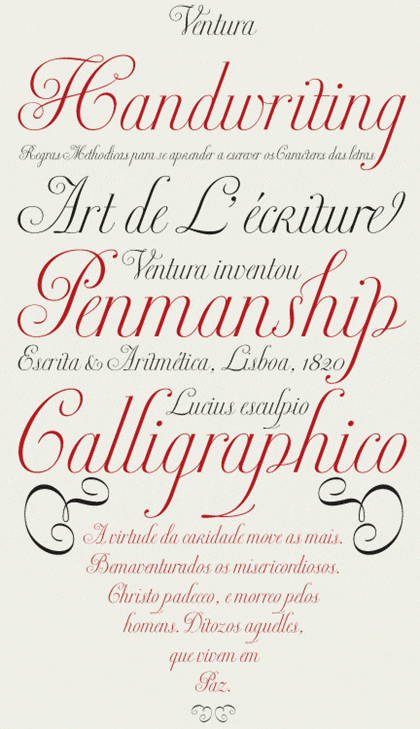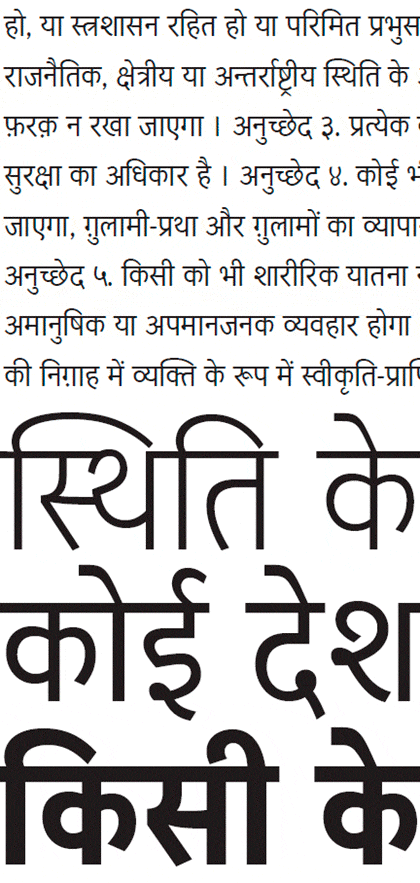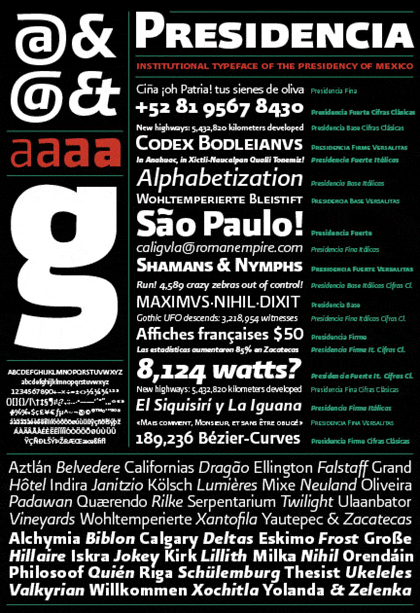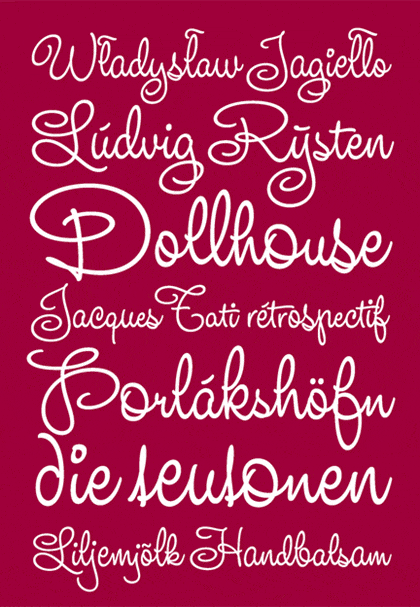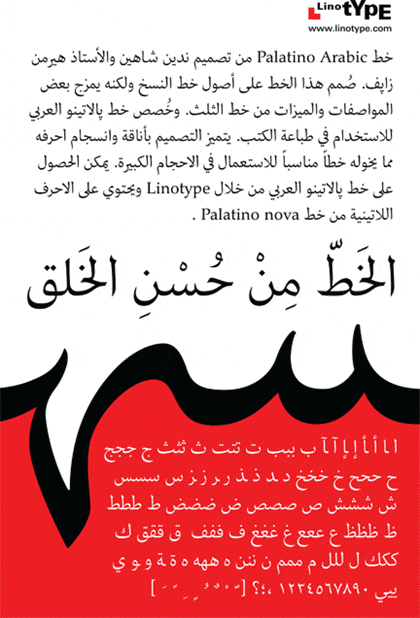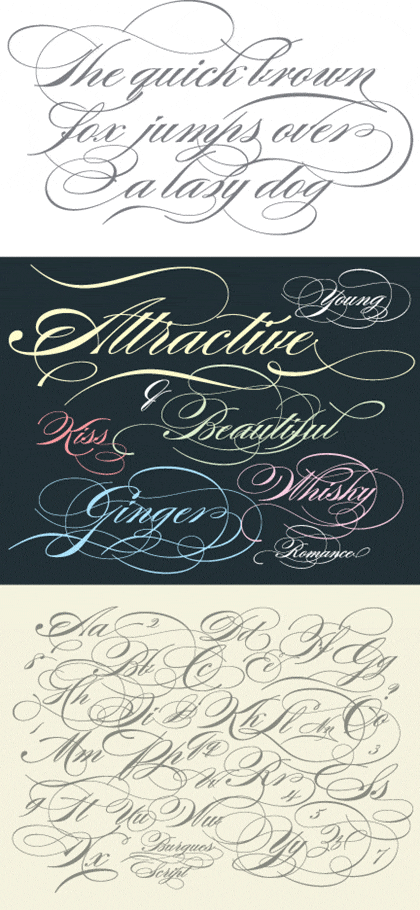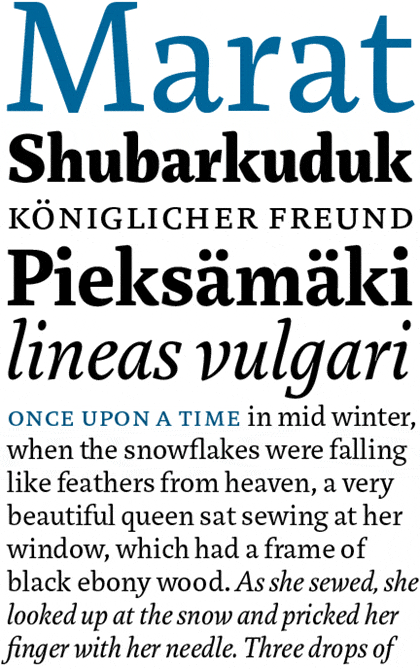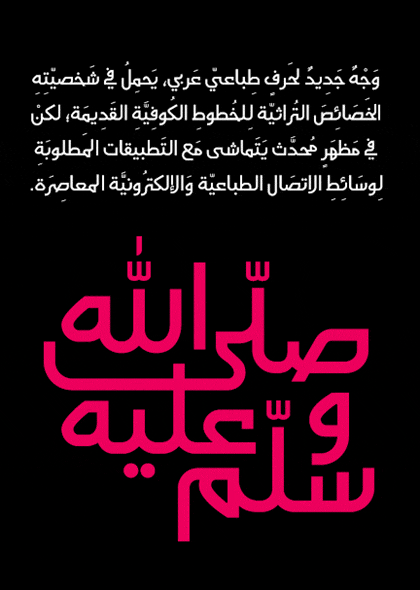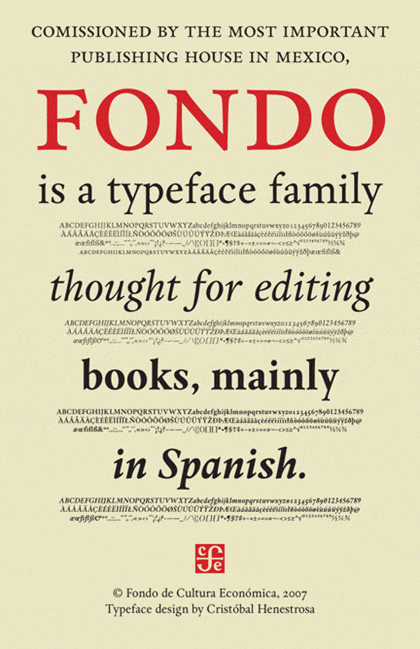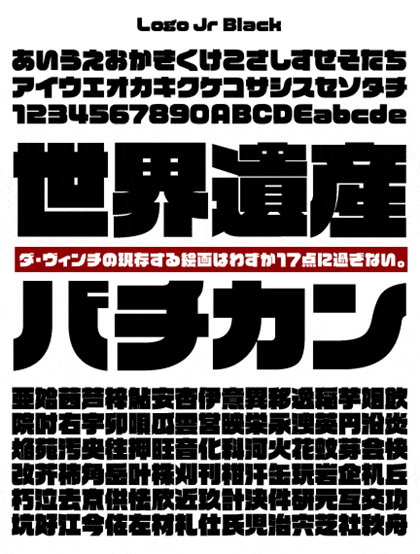
Typographie | Les lauréats Type Director Club 2008 classés par design et typo
Voici les lauréats 2008 du concours des Type Director Club de New York.
J’ai pour ma part sélectionné 14 fontes sur les 22 gagnants et placé dans l’ordre de ma préférence personnelle. C’est toujours un exercice délicat, et de sélectionner et de classer. Les critères que j’ai retenus au nombre de quatre, sont essentiellement l’originalité, la rigueur du dessin, la délicatesse et l’élégance des tracés, et enfin la difficulté du travail accompli.
La grande nouveauté depuis quelques années reste l’arrivée en force des alphabets non latins: Arabes, Chinois, Coréens, Japonais. Le caractère mobile par exemple, comme nous l’entendions lors de la conférence sur l’écriture islamique à la Galerie Anatome n’est apparu que vers la moitié du XIXe siècle dans le monde Arabe. Ce faisant les créateurs comme Fred Smeijers et Lara Assouad Khoury se penchent tels des paléontologues sur l’étude et l’adaptation de la calligraphie arabe aux styles de nos caractères latins. Une démarche d’autant plus utile que nombre d’éditions de luxe ou du commerce international ont besoin d’être composées dans plusieurs langues.
Voici le classement de Design et Typo pour
le concours 2008
Typeface: Ventura | Designer: Dino dos Santos, Matosinhos, Portugal | Foundry: DSType www.dstype.com
Typeface: Vodafone Hindi | Designers: Dalton Maag Ltd, Fiona Ross, Tim Holloway, John Hudson | London & Swells Hill, UK; | Gabriola, BC CA | www.tiro.com
Typeface: Presidencia | Designer: Gabriel Martínez, Meave | Mexico City MX | Foundry: Kimera | www.kimera.com.mx
Typeface: Studio Lettering Swing | Designer: Ken Barber,Yorklyn, Delaware | USA Foundry House Industries www.houseind.com
Typeface: Palatino Arabic | Designers: Nadine Chahine & Hermann Zapf | Bad Homburg, Germany Foundry: Linotype GmbH | www.linotype.com
Typeface: Mommie | Designer: Hubert Jocham, Memmingen, Germany | Foundry: Hubert Jocham | www.hubertjocham.de
Typeface: Burgues Script | Designer: Alejandro Paul | Buenos Aires, Argentina | Foundry: Sudtipos | www.sudtipos.com
Typeface: Marat | Designer: Ludwig Übele, Den Haag | The Netherlands Foundry | www.ludwiguebele.de
Typeface: Anselm | Designer: František Štorm | Bohemia, Czech Republic | Foundry Stormtype | www.stormtype.com/
Typeface: Al Rajhi | Designer: Habib Khoury | avantype.com | Foundry Brandinstinct: brandinstinct.com
Typeface: Restraint | Designer: Marian Bantjes & Ross Mills | BC CA | Foundry: Tiro Typeworks | www.tiro.com
Typeface: Fondo | Designer: Cristóbal Henestrosa | Mexico City, Mexico | Foundry: Estudio CH | www.estudio-ch.com
Typeface: Logo Jr Black | Designers: Shigeru Katsumoto ???, Kyoko Katsumoto ???? | Osaka, Japan | Foundry: Visual Design Laboratry Inc. | www.vdl.co.jp/
Typeface: Fresco Arabic | Designers: Fred Smeijers & Lara Assouad Khoury (Antwerp, Belium & Dubai UAE) | Foundry: The Khatt Foundation (Amsterdam, The Netherlands) | www.khtt.net